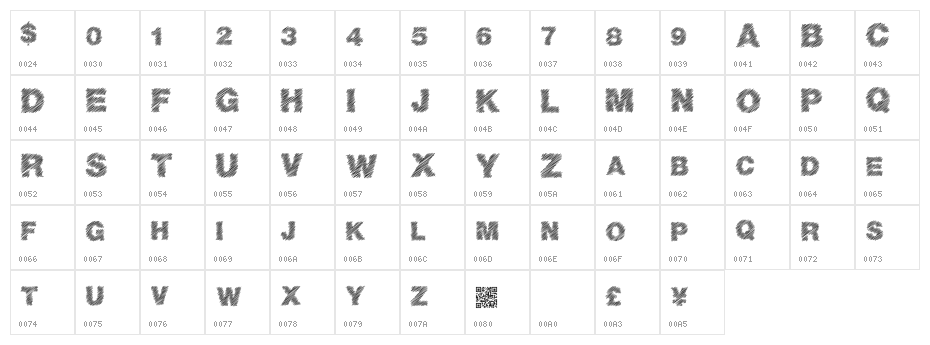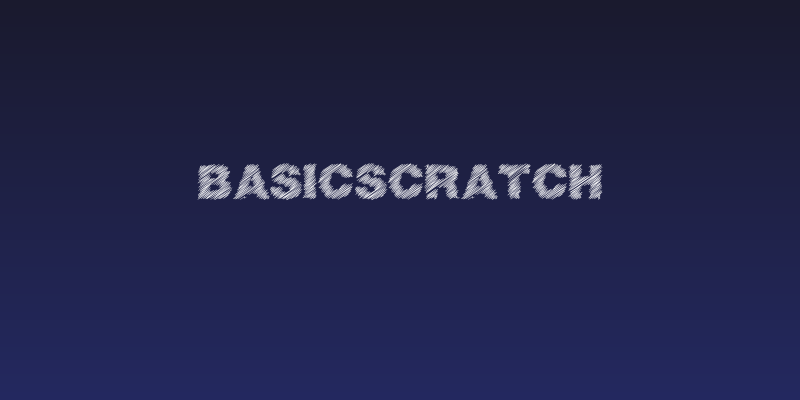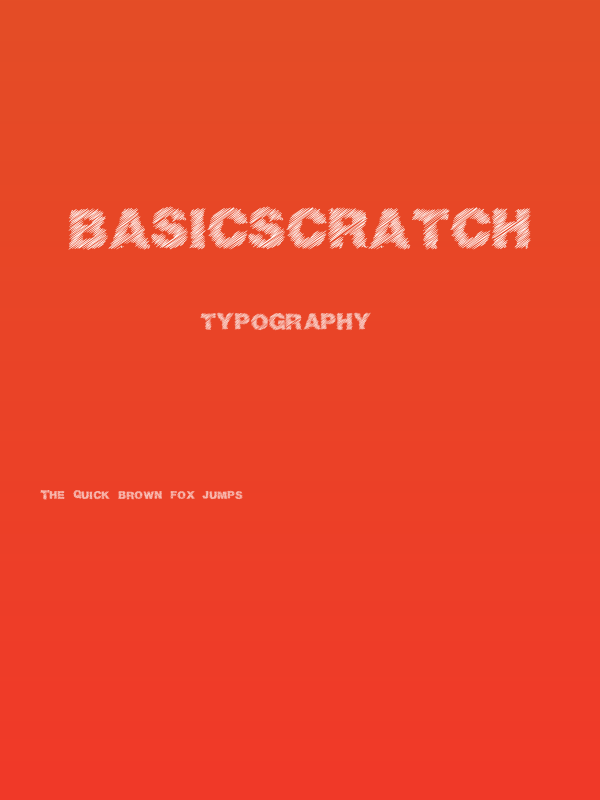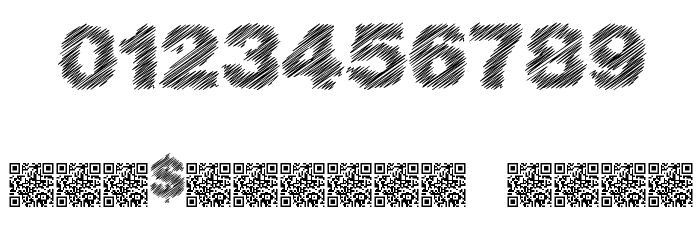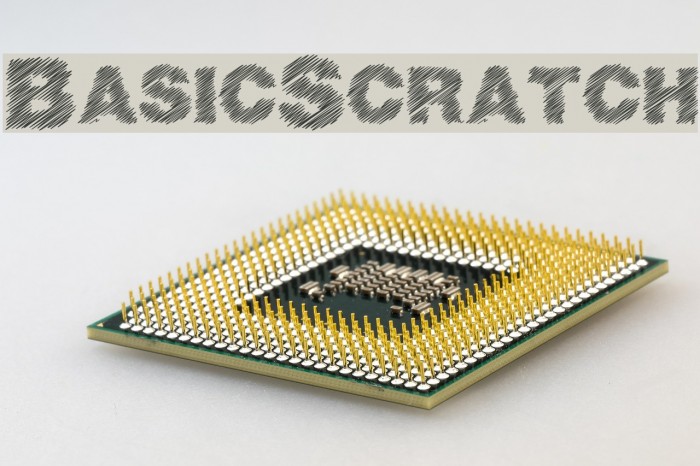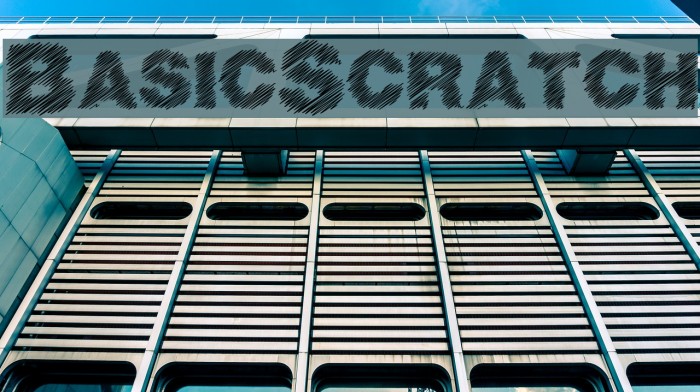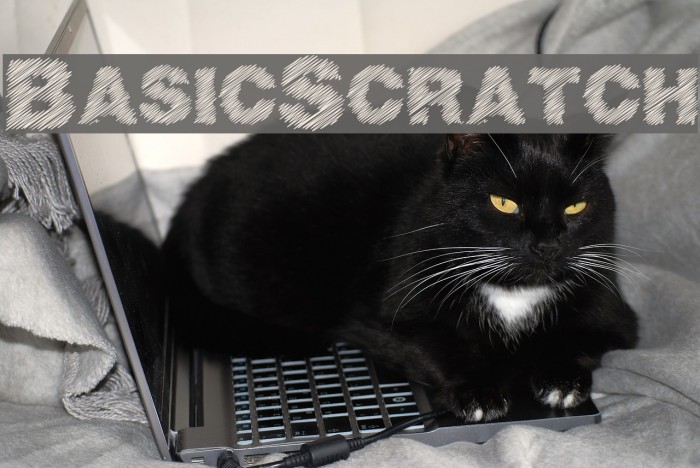
BasicScratch Font
✎ Distorted Eroded
| 分类 | Distorted Eroded |
| 整体风格 | Artistic, Energetic, Creative |
| 推荐项目 | Ideal for posters, album covers, artistic branding, and creative advertising. |